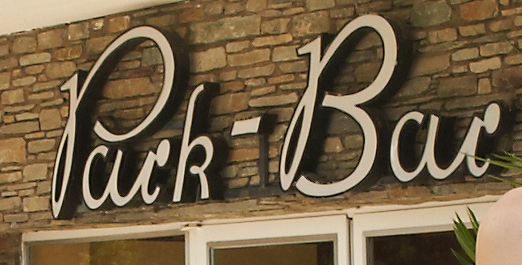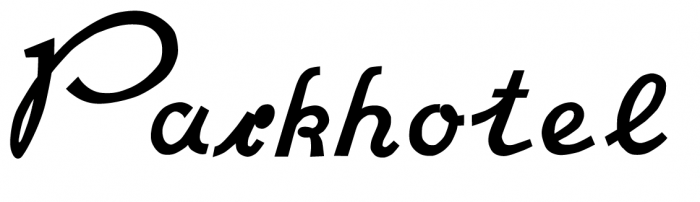
Schriftzug Parkhotel Pörtschach Österreich
Ich würde diese Schrift suchen. Es gibt leider nur einen Schriftzug der am Hotel angebracht ist. Ich habe die Schrift in Pfaden nachgezogen aber leider finde ich nichts vergleichbares und der Kunde hätte gerne genau diesen Font. Das ist allerdings in den 60er Jahren entstanden und keiner weiß von irgendwas.
Vielleicht könnt ihr mir da weiterhelfen. Auch auf Whatthefont und WhatFontis habe ich nichts vergleichbares gefunden. Liebe Grüße Ines
Wenn das aus den 60ern ist, gibt es dazu bestimmt keinen Font, da es vom Schilder- oder Lichtreklamehersteller gebaut und entworfen wurde.
Ähnliche* findet man eventuell, aber nicht ›genau diesen Font‹.  :neenee:
* eventuell hier
Wenn das aus den 60ern ist, gibt es dazu bestimmt keinen Font, da es vom Schilder- oder Lichtreklamehersteller gebaut und entworfen wurde.
Ähnliche* findet man eventuell, aber nicht ›genau diesen Font‹.  :neenee:
* eventuell hier